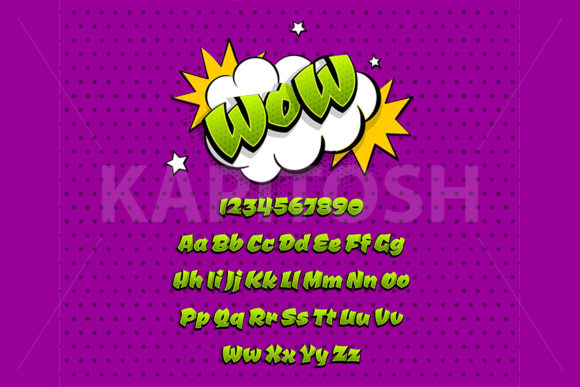
Green Lowercase and Uppercase Comic Font
Ulasan Lengkap: Green Lowercase and Uppercase Comic Font
Se você trabalha com design gráfico, publicidade ou produção de conteúdo visual, a Green Lowercase and Uppercase Comic Font é a escolha perfeita para dar vida a projetos com estilo pop‑art e super‑herói. Esta fonte combina letras minúsculas e maiúsculas em um visual comic‑book vibrante, com sombras em meio‑tom e bolhas de fala que trazem dinamismo e personalidade a qualquer composição.
- Versatilidade completa: Ideal para interiores, banners, posters, roupas, adesivos, capas de livros e muito mais.
- Design impactante: Letras em negrito com sombra halftone e balões de fala que destacam mensagens de forma divertida.
Por que escolher a Green Comic Font?
Esta fonte foi criada especialmente para quem deseja transmitir energia, humor e um toque de heroísmo nos projetos. Seu estilo único de comic book pop art se destaca em campanhas publicitárias, designs de interiores temáticos e produtos de merchandising, garantindo que sua marca ou mensagem se sobressaia na multidão.
Com a Green Lowercase and Uppercase Comic Font, você obtém uma ferramenta poderosa para transformar ideias criativas em peças visuais marcantes. Seja para uma campanha de marketing ousada, um design de camiseta estilizado ou um poster de evento, esta fonte oferece o toque profissional e divertido que seu trabalho merece.